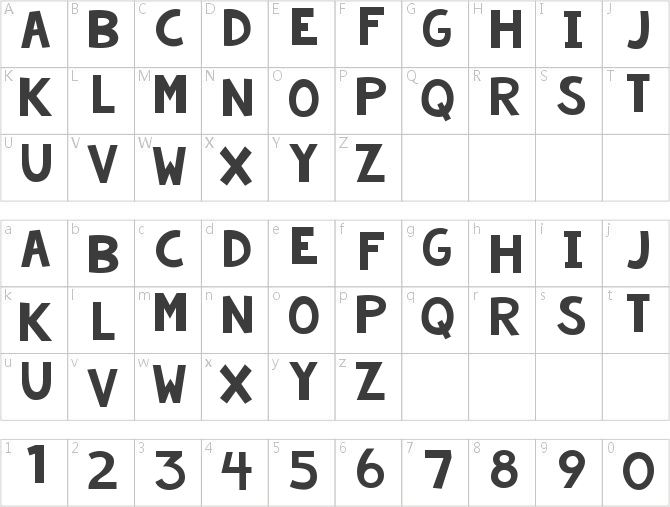
KG Summer Storm Smooth 詳情頁
KG Summer Storm Smooth字體字庫是一款讓人賞心悅目、百看不厭的英文字體,適合各類廣告和產(chǎn)品包裝設(shè)計應(yīng)用,字體大小0.03MB,格式為ttf字體,上傳用戶是小猴子1003,作者/版權(quán)方為未知